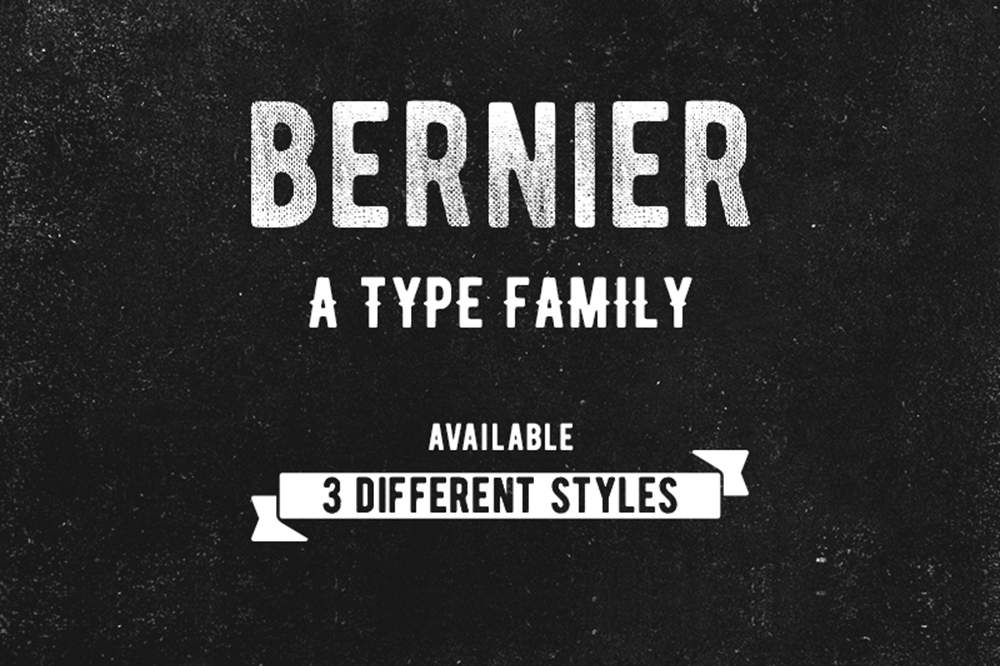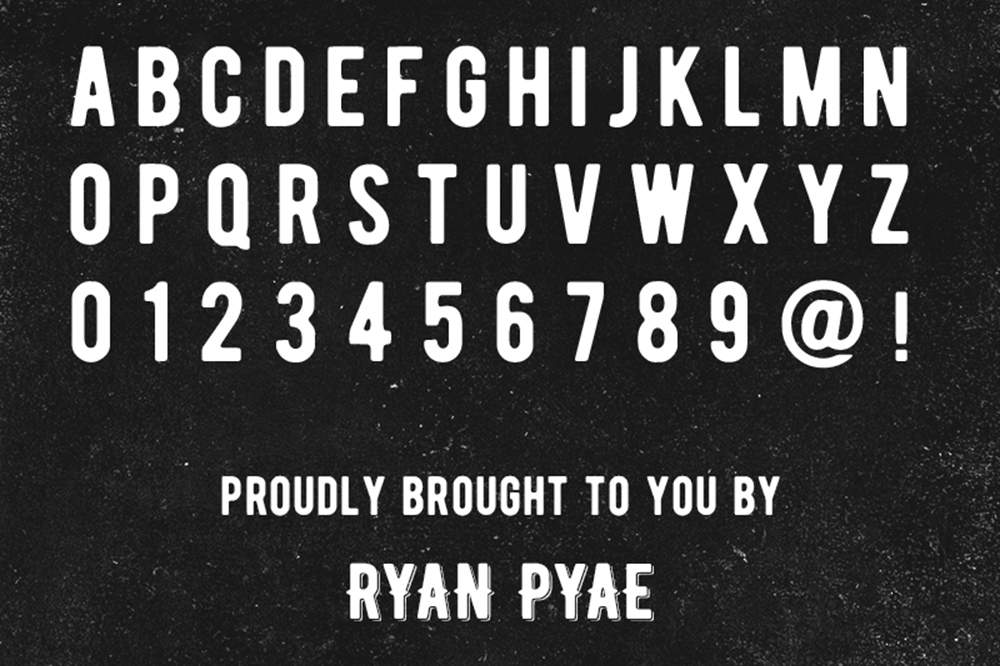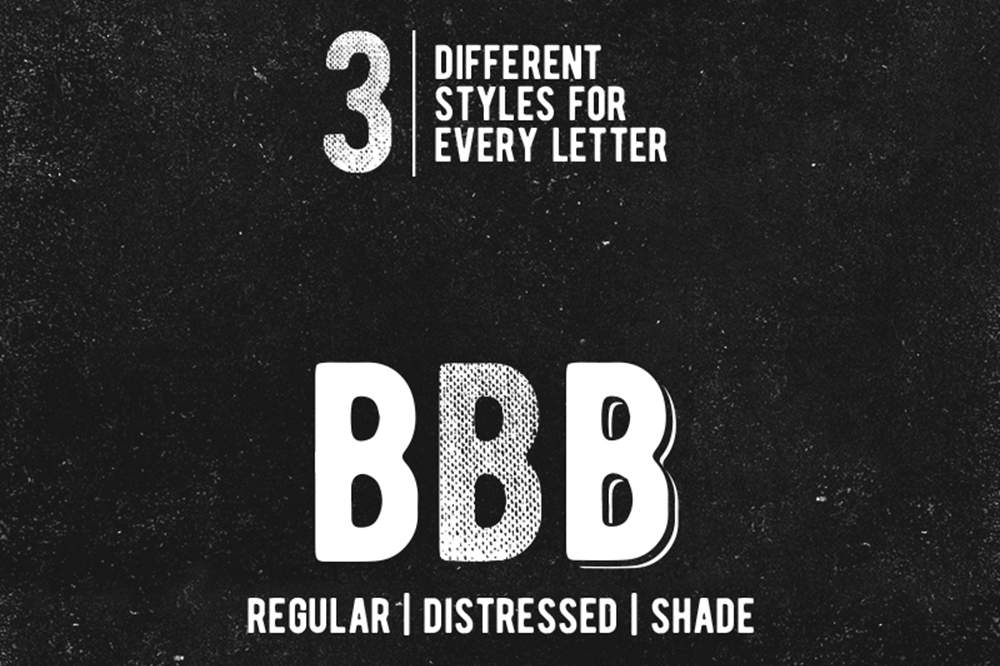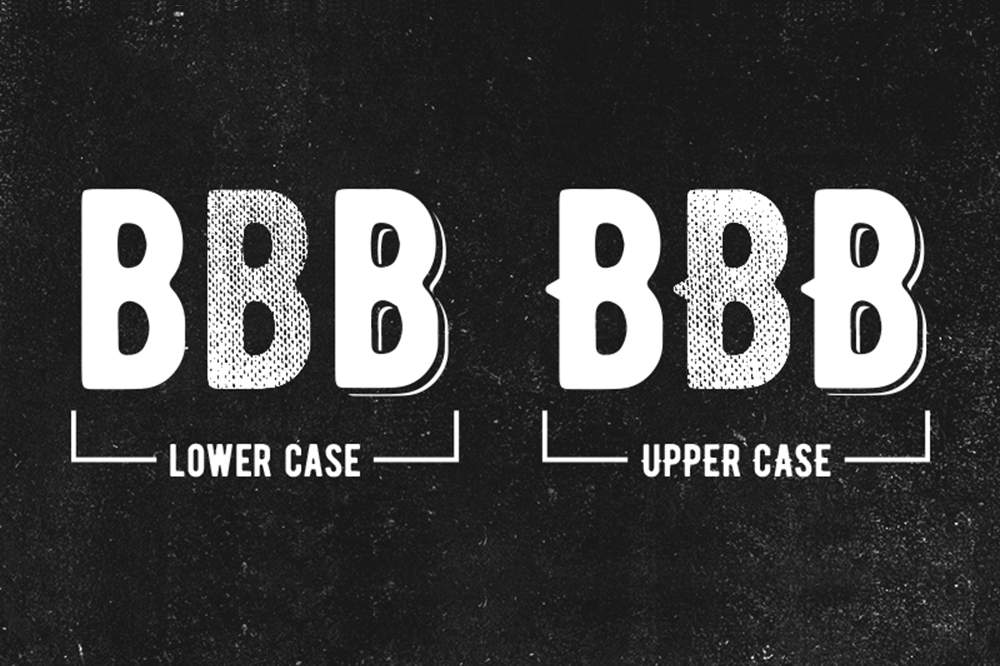
فونت پرمیوم و انگلیسی BERNIER Font برای هر نوع طراحی گرافيکی مفيد است. اين فونت برای نشانهای قديمی، تايپوگرافی به سبک قديمی و لوگوتايپ عالی است. اين فونت در 3 قالب معمولی، سايهدار و کثیف و با حروف بزرگ موجود است.
مزایای استفاده از فونت لاتین BERNIER چیست؟